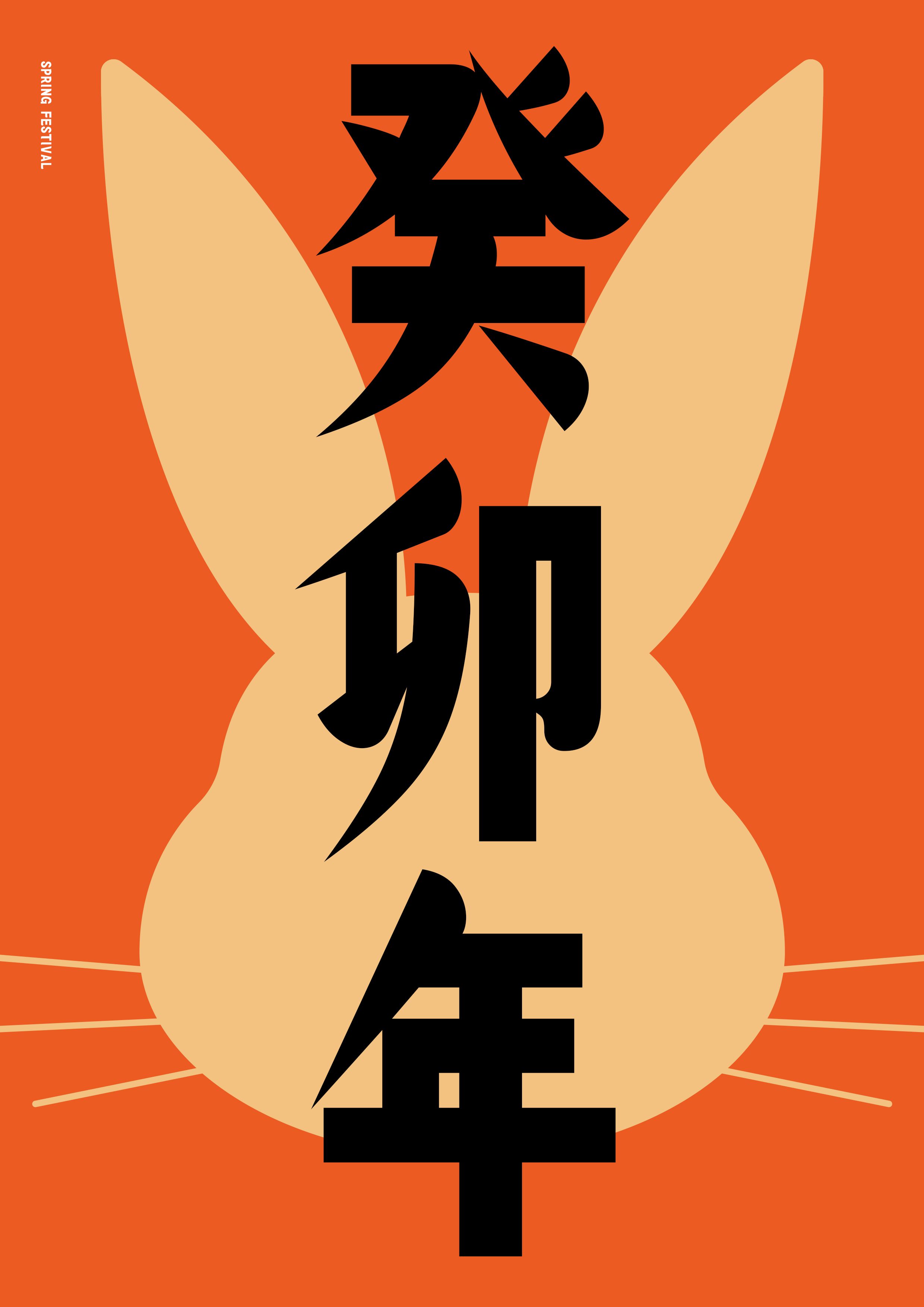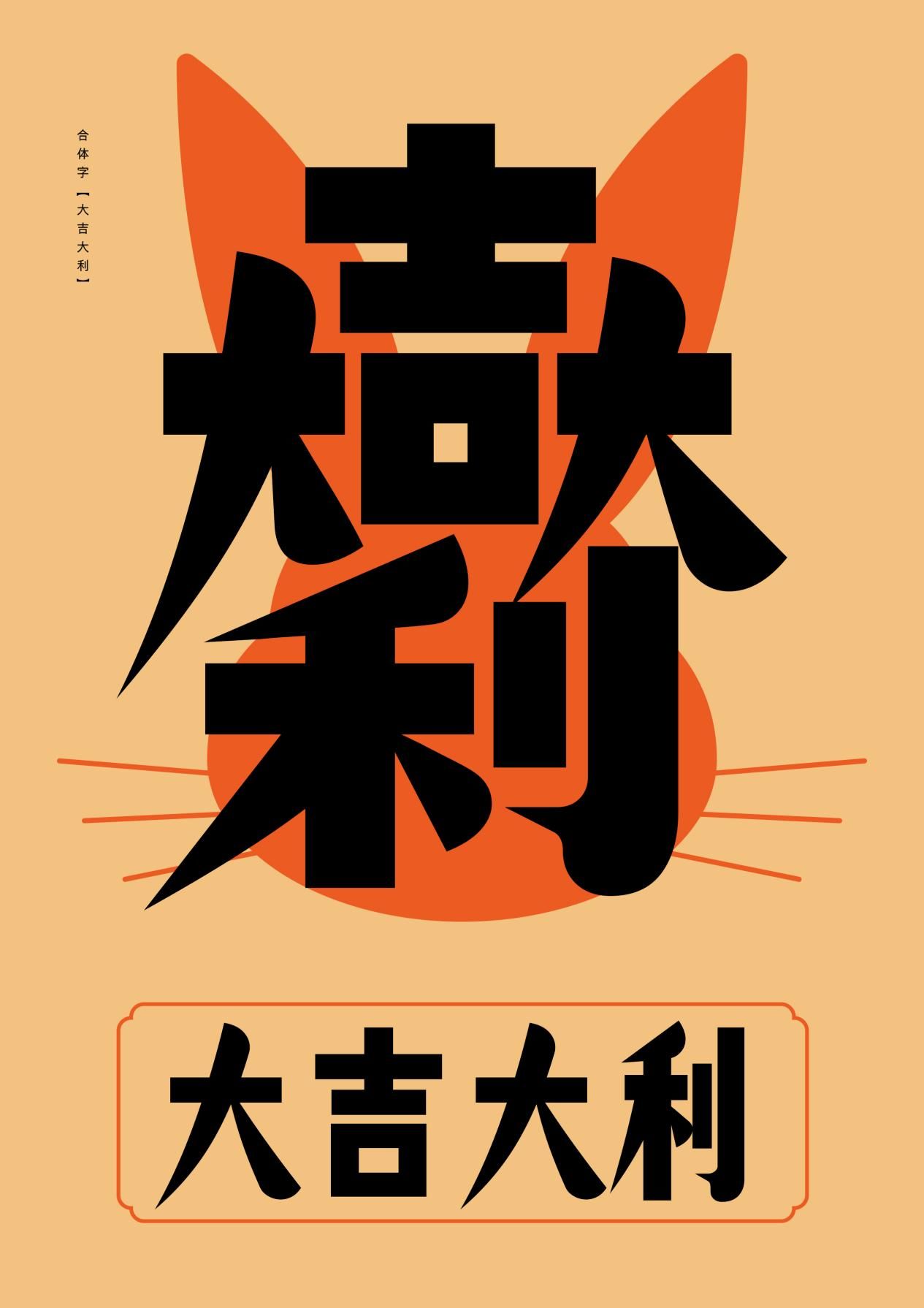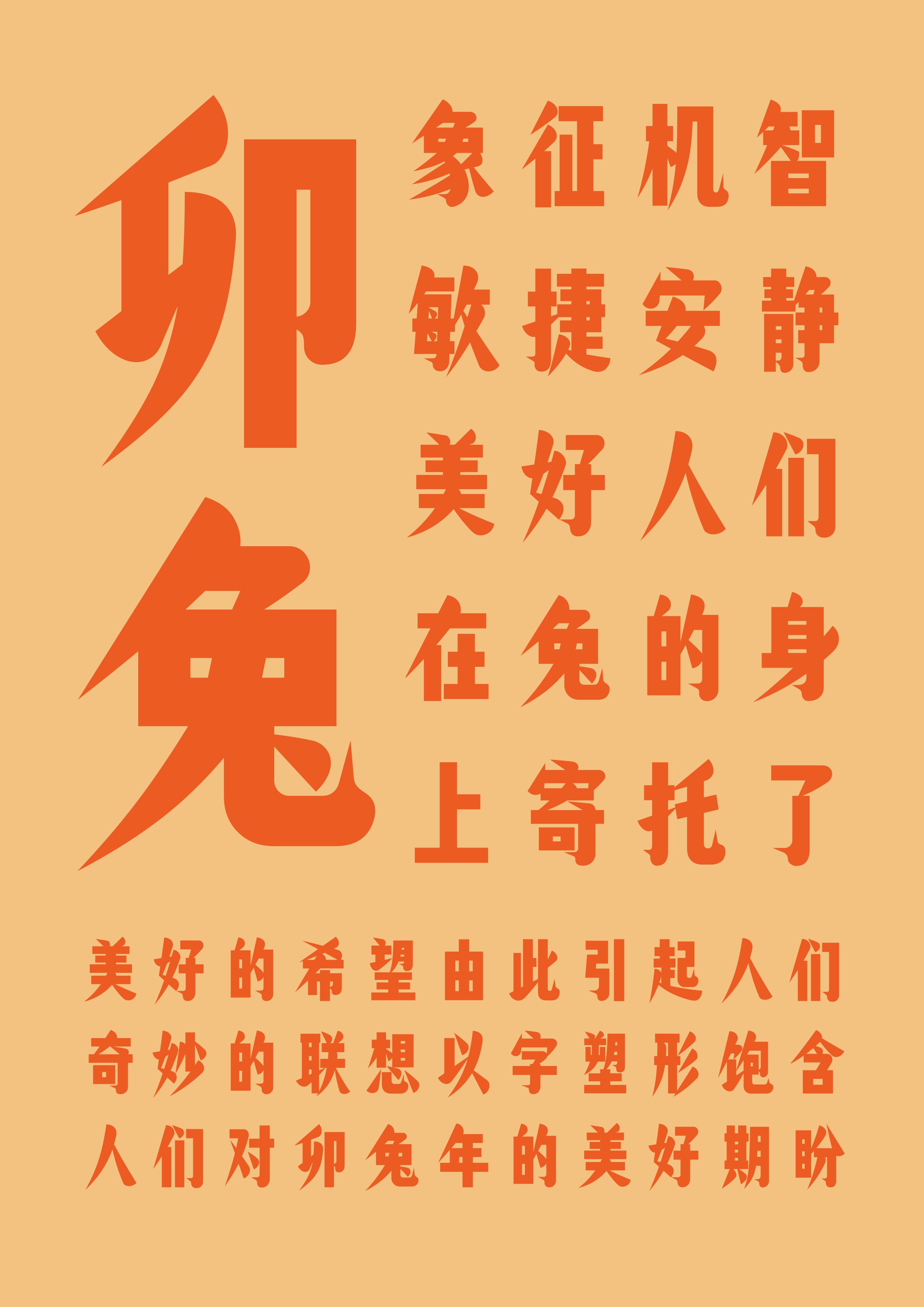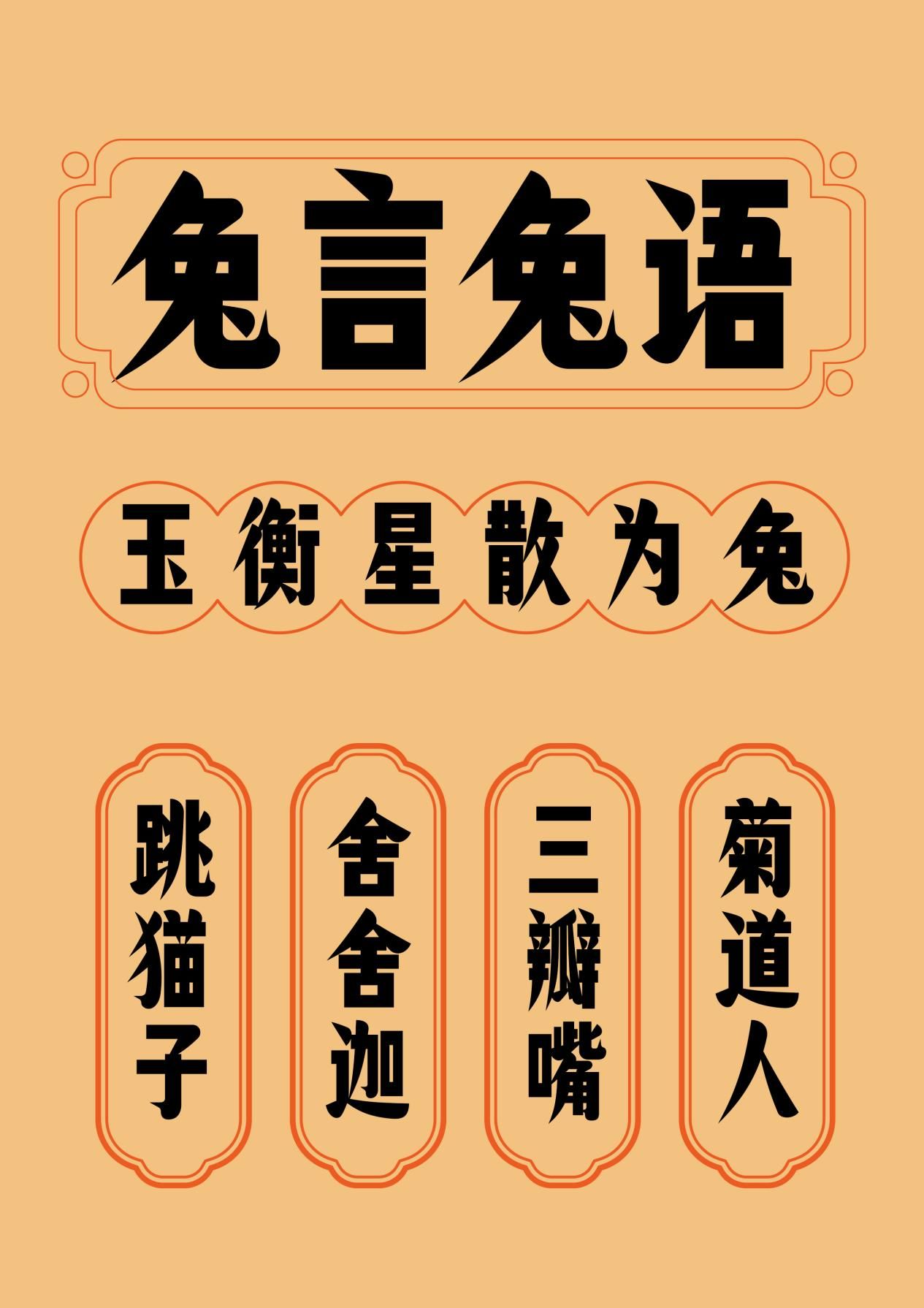
汉字之美神勇兔生肖获2023全球华人艺术设计奖(art-D Award)铜奖!
在近期的2023全球华人艺术设计奖评选中,一款独具匠心的字体——汉字之美神勇兔生肖,以其独特的设计风格和优秀的表现力,脱颖而出,获得大赛铜奖。
从字体的设计理念来看,汉字之美神勇兔生肖体的诞生,源于中国风盛行的2023卯兔年。其依托于中国十二生肖文化创作,旨在填补字体设计发展史上传统生肖文化的空缺,创造出一种充满浓厚民族色彩的文字艺术,传播独具特色的中国文化,与世界其他文明形成鲜明差异。
2023年是中国的“癸卯年”,卯作为中国十二地支的第四位,也指十二生肖中的兔。兔象征机智敏捷、安静美好,人们在“兔”的身上寄托了美好的希望,由此也引起人们奇妙的联想。
在字体的设计方面,神勇兔生肖体从刻本中挑选「卯」字造型作为灵感,其点笔灵动如兔耳,钩画团簇如兔尾。其中宫紧缩,重心上提,但区别于传统结构,整体上部收而下盘舒张,以巧妙的表现形式呈现出卯兔的形象,同时融合黑体基因于直画,创新简约的横竖笔画使卯兔的视觉形象更显现代灵巧,亦为探索字体造型设计上的无穷变化。
汉字之美神勇兔生肖体以字塑形,演绎21世纪全新的兔年生肖形象,饱含人们对卯兔年的美好期盼。
汉字之美神勇兔生肖体,以其独特的设计理念和出色的表现力,为设计师们带来了更多的探索和思考空间,也为设计行业注入了更多的新鲜血液。相信在未来的设计创作中,这款字体也将继续发挥着重要的作用,为设计带来更多的美感和灵感。